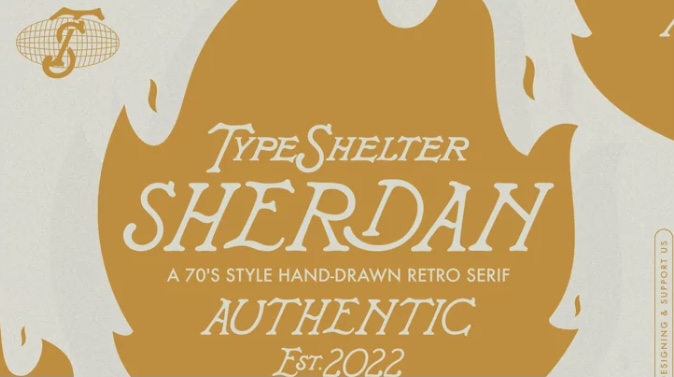
Sherdan - это ретро-засечка в стиле 70-х годов, нарисованная от руки. Поставляется со стандартными символами, цифрами и пунктуацией. Подходит для таких целей, как вывеска, плакат, логотип, этикетка, заголовок, дизайн обложки и т.д.